Hello Autumn Hand Drawing Caliigraphy
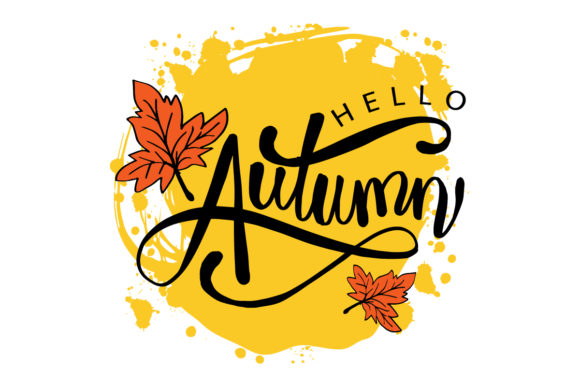
Om du letar efter högkvalitativa tillgångar som Hello Autumn Hand Drawing Caliigraphy, är detta premiumpaket ett fantastiskt val för dina kreativa projekt.
Oavsett om du skapar POD-produkter (Print on Demand), bröllopsinbjudningar eller grafik för sociala medier, är Hello Autumn Hand Drawing Caliigraphy ett perfekt val.